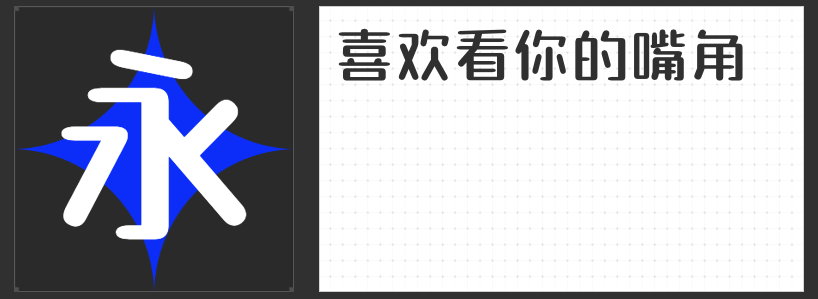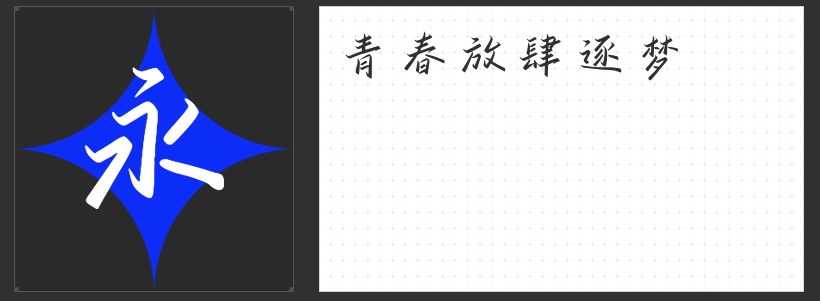
四款印刷设计精品字体推荐:让视觉表达更具张力与温度
在印刷设计的世界里,字体不仅是信息传递的媒介,更是情感与风格的载体。选择一款契合主题的字体,能让作品在瞬间抓住观者的目光。以下四款兼具美学价值与实用性的字体,以其独特的设计语言,为印刷设计注入鲜活的生命力。
一、字青春悸动简 常规
这款字体以清秀别致的气质脱颖而出。其字形结构端正,笔画粗细均匀且清晰利落,整体呈现出一种克制而不失灵动的平衡感。无论是作为短视频的标题字,还是海报中的核心文案,它都能以简洁的视觉语言传递信息,同时通过微妙的笔画弧度与空间布局,营造出清新自然的氛围,适用于需要突出内容但避免过度装饰的场景。
二、励字造仲夏简 常规
当传统书法的韵味邂逅现代设计的简洁,这款字体应运而生。笔画坚挺爽利,边缘的斑驳处理赋予其手写般的温度,而钩笔的洒脱收尾则强化了力量感。字形端正中透露出随性,既能驾驭商业海报的视觉冲击,也能融入包装设计的细腻叙事,甚至在新媒体传播中通过动态效果展现笔触的韵律,实现多场景的无缝适配。
三、字青春逐梦简 准粗
作为一款文艺手写字体,它以“准粗”的笔画宽度平衡了随性与稳重。字形端正却不失灵动,笔画间的自然起伏与留白处理,营造出放松治愈的视觉体验。无论是作为标题的视觉焦点,还是内文排版的层次点缀,它都能以温暖的笔触拉近与观者的距离,尤其适合需要传递人文关怀或情感共鸣的设计场景。
四、励字笑语声声简
这款字体以童趣为核心设计语言,笔画圆润如孩童的涂鸦,转角处的弧线处理与均匀的布白,让每个字符都仿佛在微笑。其辨识度极高的字形结构,既能完美融入二次元的活泼语境,也能为三次元的商业设计增添萌动气息。从儿童产品包装到社交媒体表情包,它以“无尖锐边角”的亲和力,唤醒观者内心深处的纯真记忆。
这四款字体各具特色,却共同诠释了印刷设计中“形式与功能统一”的精髓。它们不仅是工具,更是设计师表达态度的语言,让每一次排版都成为与观者的对话。